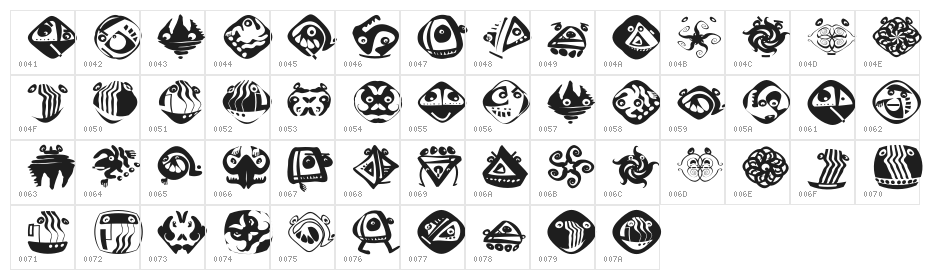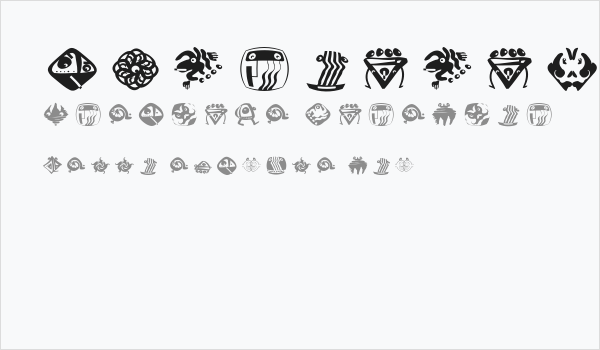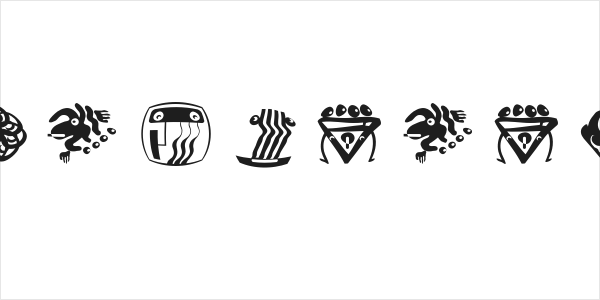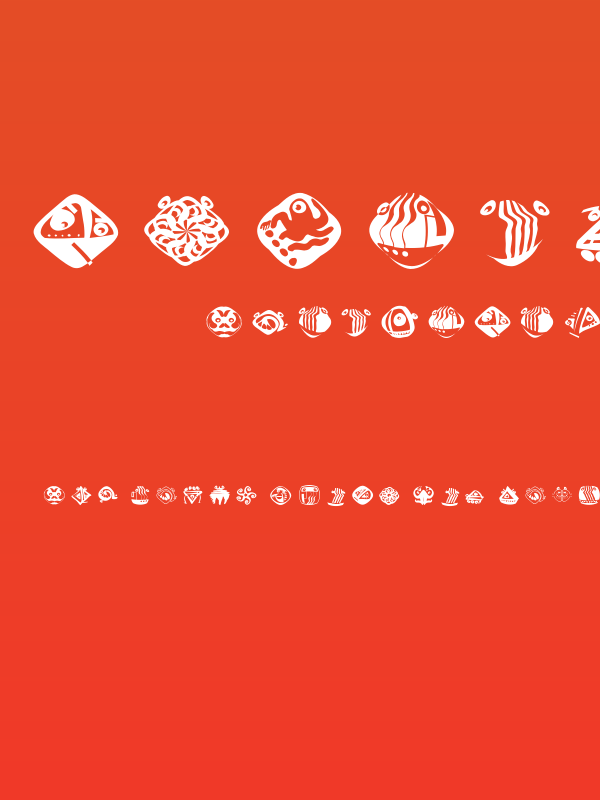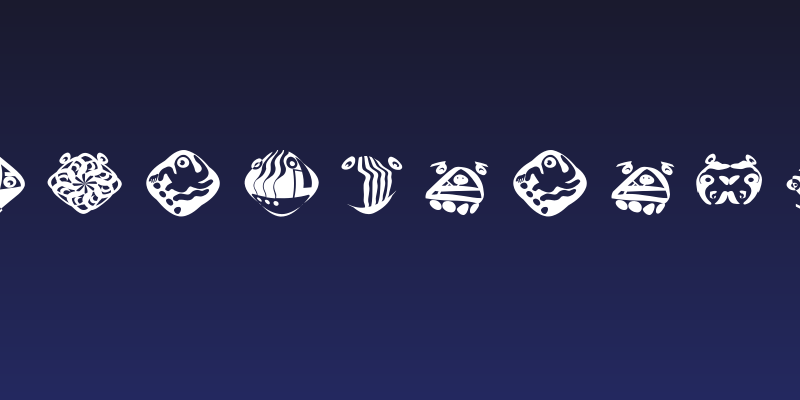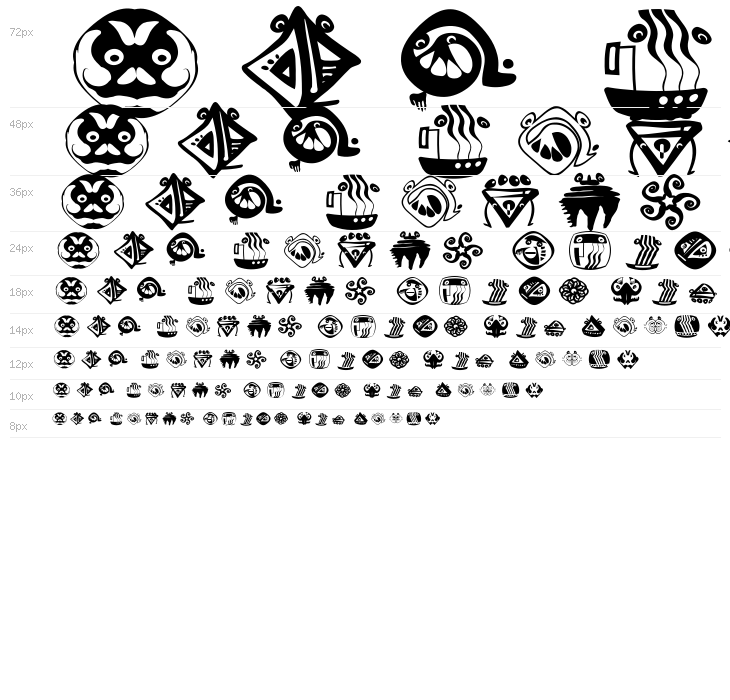
Androidish Font
| Caso d'uso | Logos, Artistic designs, Illustrations |
| Progetti proposti | Ideal for creative projects such as logo design, branding for playful or artistic brands, children's book illustrations, or unique graphic design elements. |